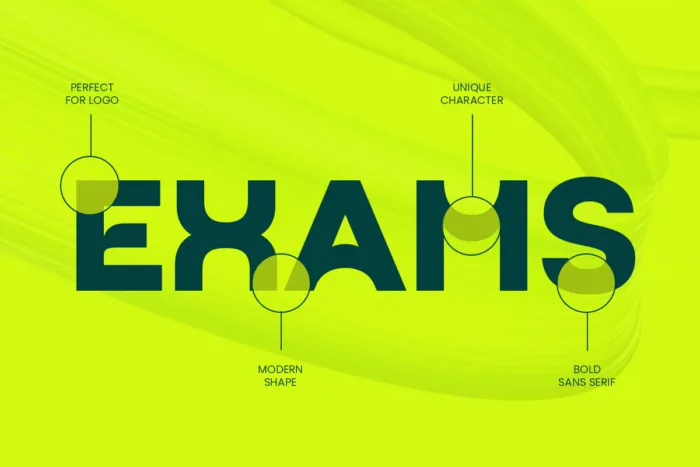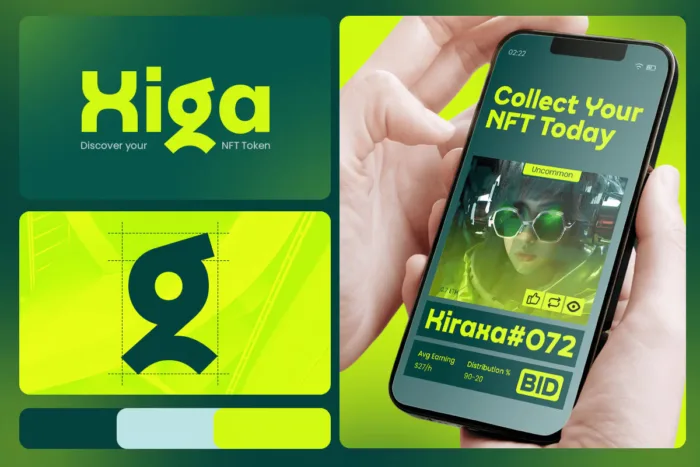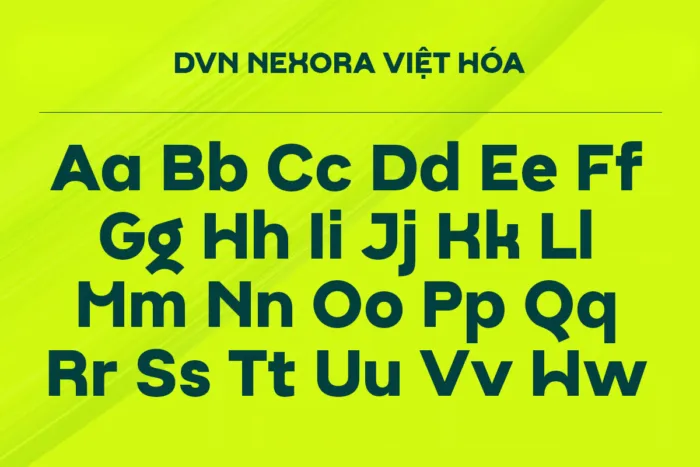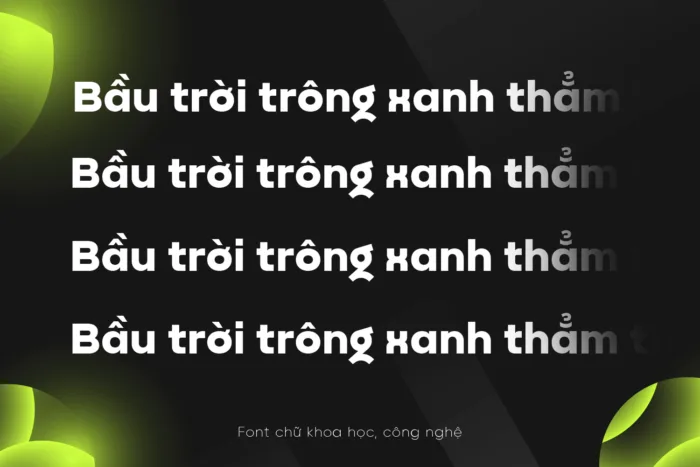
DVN Nexora Việt hóa – Font sans-serif hiện đại, hình học và phá cách
DVN Nexora là một phông chữ sans-serif mang phong cách hình học hiện đại, được thiết kế với tinh thần tối giản nhưng đầy cá tính. Font sở hữu những đường nét gọn gàng, mạch lạc và có tiết tấu hình học ổn định, giúp dễ dàng tạo nên bố cục mạnh mẽ và chuyên nghiệp. Với tinh thần thiết kế đương đại, Nexora phù hợp cho các dự án liên quan đến công nghệ, sáng tạo, truyền thông hoặc thương hiệu hướng đến sự trẻ trung và khác biệt.
DVN Nexora hỗ trợ đầy đủ tiếng Việt, đảm bảo khả năng ứng dụng linh hoạt cho cả thiết kế in ấn lẫn giao diện số. Đây là lựa chọn lý tưởng cho nhà thiết kế đang tìm kiếm một phông chữ vừa hiện đại vừa mang bản sắc riêng biệt, dễ ghi nhớ và tạo dấu ấn thị giác.